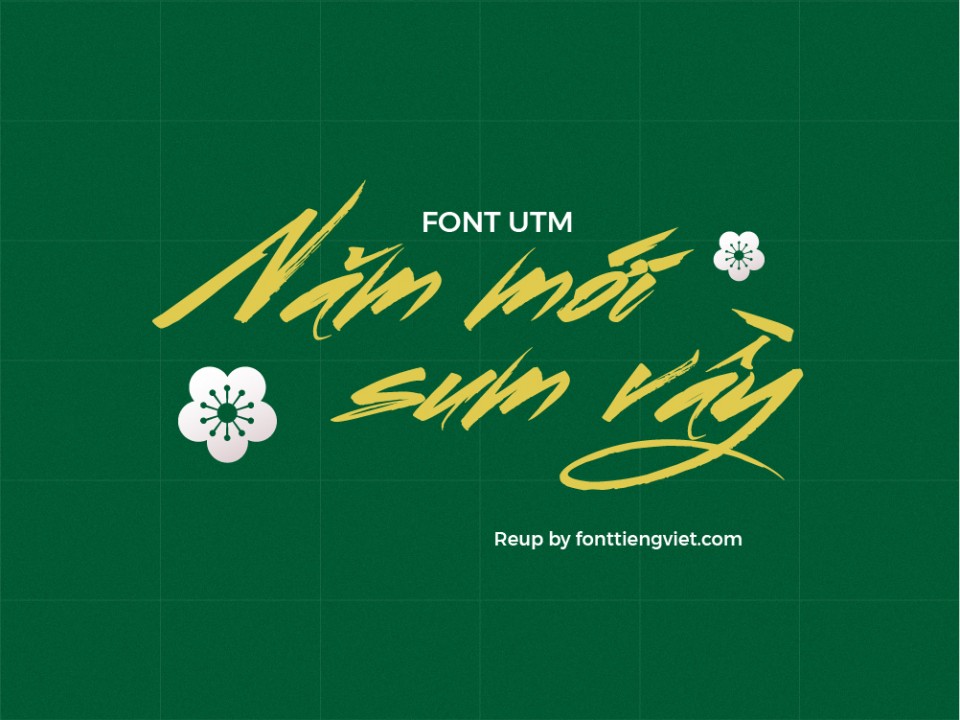
Font việt hóa UTM Ông Đồ Trẻ – Tết
Trong thế giới thiết kế đồ họa Việt Nam, việc tìm kiếm một mẫu Font Miễn Phí mang đậm bản sắc dân tộc là điều vô cùng cần thiết. Font việt hóa UTM Ông Đồ Trẻ – Tết là một trong những bộ phông chữ thư pháp hiện đại được ưa chuộng nhất hiện nay. Với những nét bút uyển chuyển nhưng không kém phần trẻ trung, bộ chữ này đã thổi một luồng gió mới vào các tác phẩm nghệ thuật truyền thống, giúp người dùng dễ dàng tạo nên những sản phẩm ấn tượng cho dịp đầu năm mới.
Ưu điểm nổi bật của Font việt hóa UTM Ông Đồ Trẻ – Tết
Bộ phông chữ này sở hữu phong cách thư pháp độc đáo, mô phỏng lại nét vẽ tài hoa của những ông đồ thời hiện đại. Điểm đặc biệt của nó là sự cân bằng giữa tính nghệ thuật và khả năng hiển thị rõ ràng trên nhiều nền tảng khác nhau.
Ứng dụng đa dạng trong thiết kế đồ họa
Người dùng thường lựa chọn Font việt hóa UTM Ông Đồ Trẻ – Tết để thiết kế các mẫu thiệp chúc mừng, bao lì xì hay các banner quảng cáo sự kiện Tết. Nhờ được việt hóa chuẩn xác, bạn sẽ không gặp phải lỗi gõ dấu hay các ký tự đặc biệt trong tiếng Việt. Điều này giúp quá trình sáng tạo trở nên mượt mà và chuyên nghiệp hơn rất nhiều.
Cách sử dụng phông chữ hiệu quả cho người mới
Để phát huy tối đa vẻ đẹp của bộ chữ, bạn nên kết hợp với các tông màu truyền thống như đỏ, vàng hoặc xanh lá cây. Ngoài ra, việc sử dụng các hình ảnh minh họa như hoa mai, hoa đào sẽ tạo nên một tổng thể hài hòa, mang đậm không khí lễ hội cổ truyền của người Việt Nam.